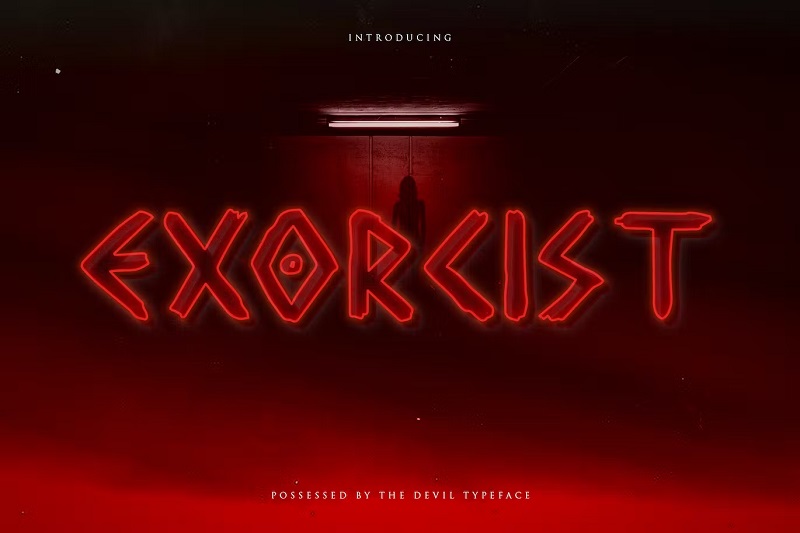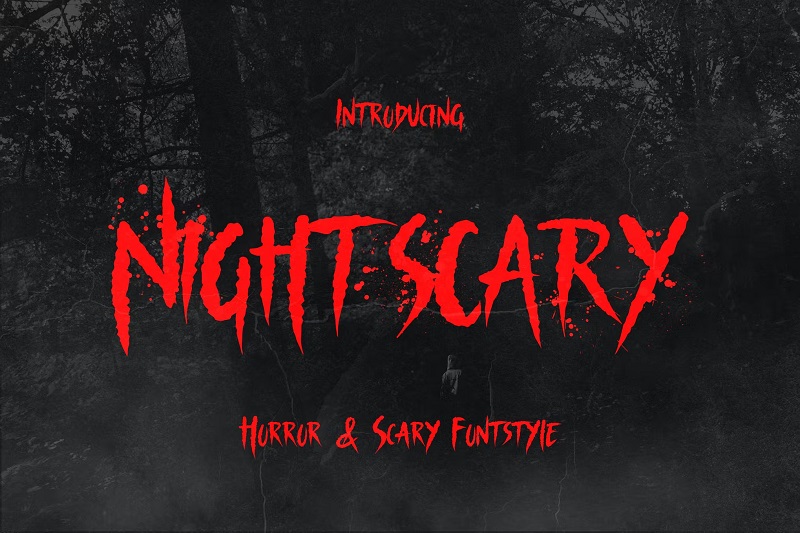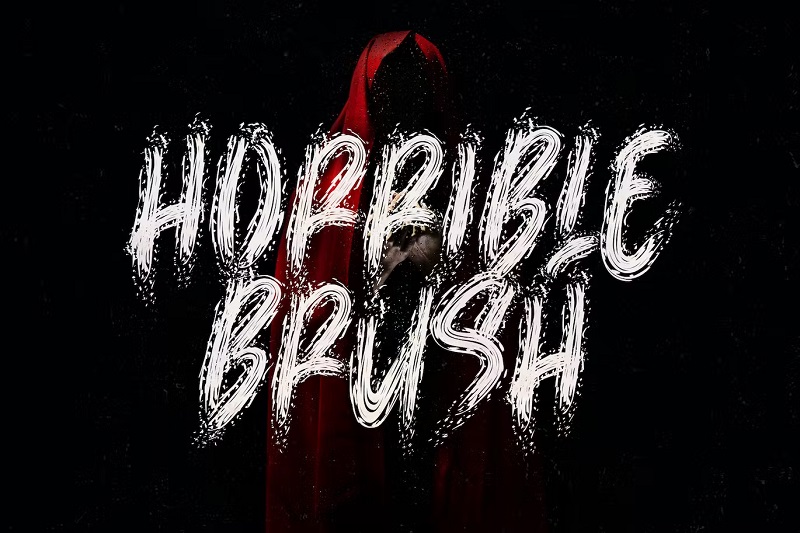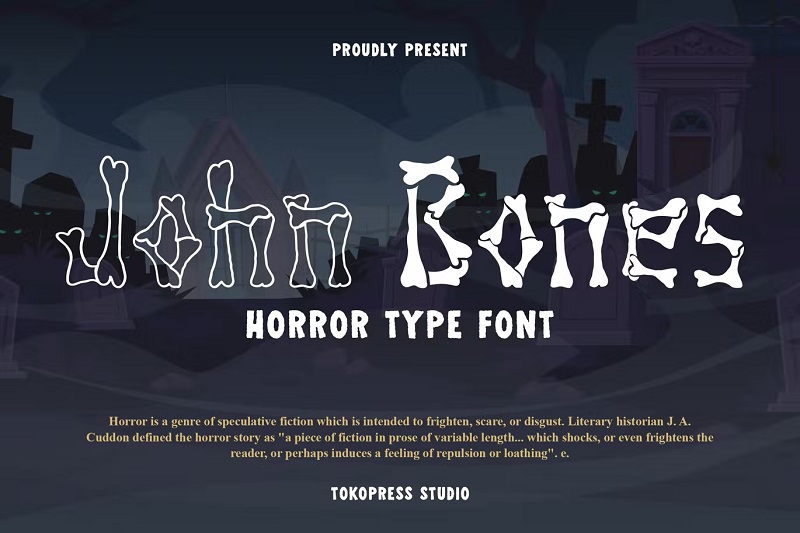
31 Horror-Schriftarten für wirklich gruselige Designs – 2024
Veröffentlicht: 2024-01-15Die besten Schriftarten rufen Emotionen hervor – und diese haarsträubenden Horror-Schriftarten lassen Ihnen garantiert einen Schauer über den Rücken laufen.
Wir haben den Markt durchforstet, um die allerbesten Horror-Schriftarten herauszusuchen, damit Sie das nicht tun müssen. Schauen Sie sich gerne die Liste unten an und klicken Sie darauf, wenn Sie eine Schriftart sehen, die Ihnen ins Auge fällt, um zur Download-Seite zu gelangen.
Und keine Sorge, wir haben darauf geachtet, eine Mischung aus verschiedenen Schriftarten und Stimmungen einzubinden, sodass hier für jede Art von Projekt etwas Passendes dabei sein sollte.
Egal, ob Sie an einem Halloween-Produkt-Branding, einem Horrorfilm-Poster, einem gruseligen Buchcover oder einer anderen Art von gruseligem Kunstwerk arbeiten, auf dieser Liste sollten Sie etwas finden, das zu Ihnen passt.
Lass uns anfangen!
Was sind Horror-Schriftarten?
Horror-Schriftarten sind Schriftarten, die Elemente des Horror-Genres enthalten. Sie sind bewusst so gestaltet, dass sie Angst hervorrufen und Sie an Geister, Gespenster und Dinge denken lassen, die im Dunkeln herumschleichen.
Bei Horror-Schriftarten kann es sich um jede beliebige Schriftklassifikation handeln: Serifenschrift, serifenlose Schriftart, Experimentalschrift, Skriptschrift, Blackletter-Schriftart … Alles ist möglich – solange es gruselig ist!
Wir haben uns auch entschieden, weniger gruselige Schriftarten in diese Liste aufzunehmen, die dennoch ein Horrorthema haben, wie zum Beispiel Halloween-Schriftarten für Kinder.
Die 31 besten Horror-Schriftarten (kostenlos und kostenpflichtig)
1. Horror Joys – Unsere Top-Wahl
Horror Joys ist eine gruselige Schriftart, die von Horrorfilmen inspiriert ist. Die groben handgezeichneten Buchstabenformen weisen alle Merkmale einer gruseligen Schriftart auf. Es enthält alle üblichen Glyphen: Großbuchstaben, Kleinbuchstaben, Zahlen und Satzzeichen sowie ein Bonuspaket.
Warum es unsere erste Wahl ist:
Der Grund, warum wir Horror Joys mögen, ist seine Vielseitigkeit. Es ist die perfekte Wahl für alle Ihre Horror-Designs, von Filmplakaten bis hin zu Death-Metal-Albumcovern und allem dazwischen.
2. Gruselige Dinge
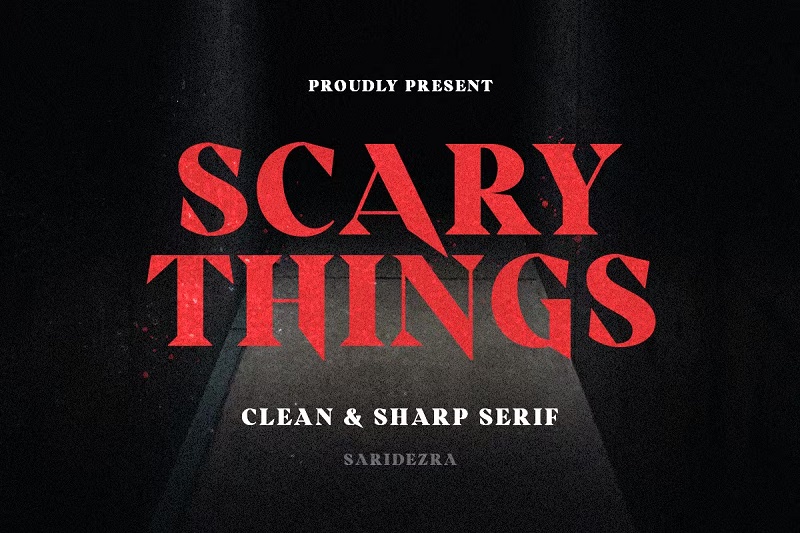
Scary Things ist eine klare und scharfe Serifenschrift des Designers Saridezra. Die scharfen Kanten der Glyphen erinnern an Dolche, Dracula und andere Tiere mit Reißzähnen. Die dicke Strichstärke und die geraden Linien sorgen dafür, dass diese Schriftart gut lesbar ist und auf allen Arten von Designs gut aussieht, sich aber besonders gut für Thriller- und Horrorfilme sowie Buchcover eignet.
3. Sadistisch
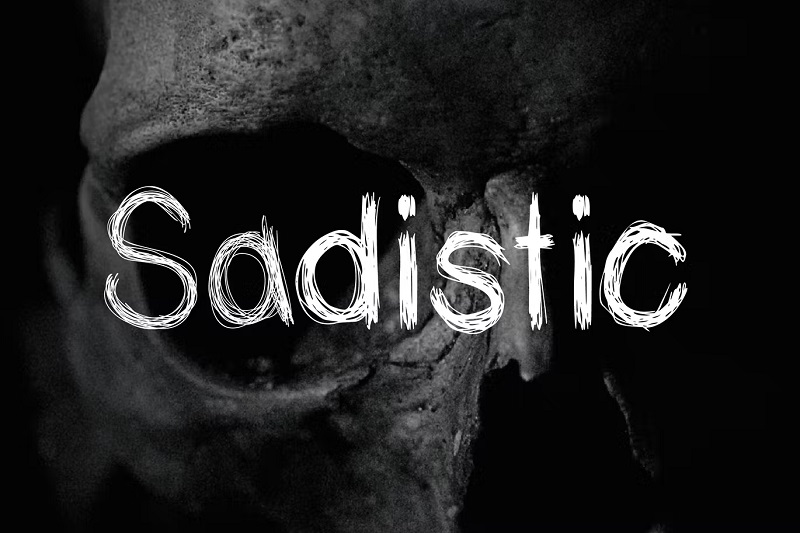
Sadistisch ist genauso erschreckend, wie es klingt. Es ist eine böse aussehende Schriftart mit Glyphen, die so gestaltet sind, als wären sie von einem wahnsinnigen Mörder immer wieder mit einem scharfen Gegenstand in das Papier geritzt worden.
4. Flucht!
Flucht! Ist eine weitere einzigartige Horror-Schriftart mit einem coolen, retro-inspirierten Stil. Es eignet sich perfekt für Death-Metal-Kunst, Retro-Horrorfilm-Cover und andere kreative Designprojekte. Es ist in zwei Versionen erhältlich: normal und schräg. Zusätzlich zur Schriftart selbst enthält der Download auch einige kostenlose Bonus-PSD-Illustrationen und Hintergründe, die Sie Ihren Designs hinzufügen können.
5. Pandora
Pandora ist eine unheimliche, seltsame Schriftart mit etwas ausgesprochen Düsterem. Es zeichnet sich durch seltsame Formen und eine Fülle unnötiger Querbalken und Linien aus, die auf das Okkulte hinweisen. Es gibt es in drei Versionen: Ep.1, Ep.2 und Ep.3. Jede weitere Episode wird immer seltsamer. Es handelt sich um eine Großbuchstabenschrift, die Ziffern, aber keine anderen Glyphen enthält.
6. Gendarwo
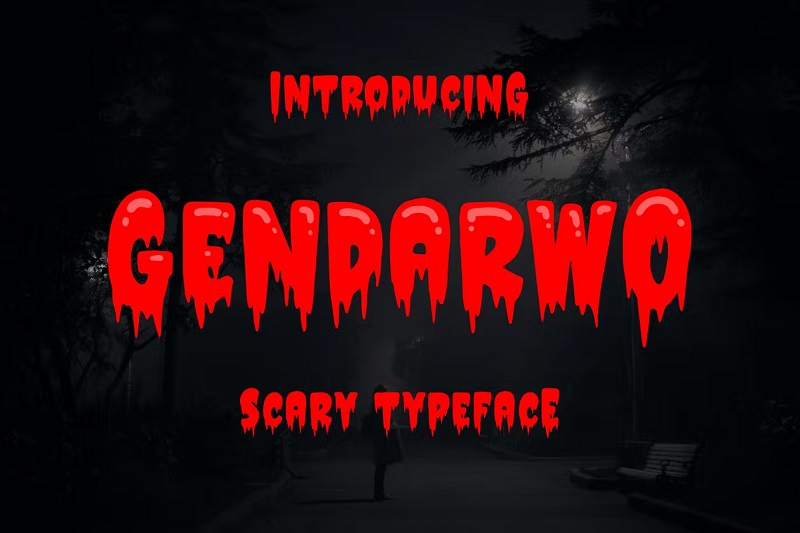
Gendarwo ist eine gruselige Schrift, die aussieht, als würde Blut tropfen – oder vielleicht auch Schleim. Auf jeden Fall ist es auf jeden Fall gruselig. Obwohl es dort definitiv ein Horror-Thema gibt, ist dieses nicht ganz so furchteinflößend wie einige der anderen Schriftarten auf dieser Liste.
Es ist ein kleines Klischee und nimmt sich selbst nicht allzu ernst, was es zu einer guten Wahl für lässigere und lustigere Horror-Designs macht, wie Spukhäuser, Flyer für Halloween-Partys und gruselige Bücher für Kinder.
7. Astrobia
Astrobia ist eine moderne, futuristische Schriftart mit minimalistischem Stil. Es eignet sich perfekt für Cover von Science-Fiction-Horrorbüchern und -Filmen, da es an Außerirdische und interdimensionale Wesen erinnert. Es ist in 6 verschiedenen Ausführungen und 3 Gewichten erhältlich. Sie können Stile kombinieren und kombinieren, um einen Kontrast in Ihren Designs zu schaffen.
8. Yokai
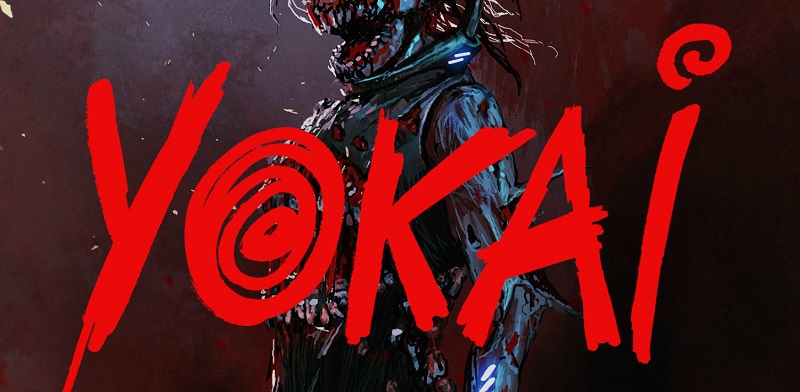
Yokai ist eine einzigartige grobe Pinselschrift, die kostenlos erhältlich ist. Der Schriftname „Yokai“ bezieht sich auf übernatürliche Geister und Wesenheiten, die in der japanischen Folklore weit verbreitet sind. Und getreu ihrem Namen hat diese Schriftart definitiv etwas Übernatürliches und Fremdartiges.
Überprüfen Sie die Schriftartenlizenz